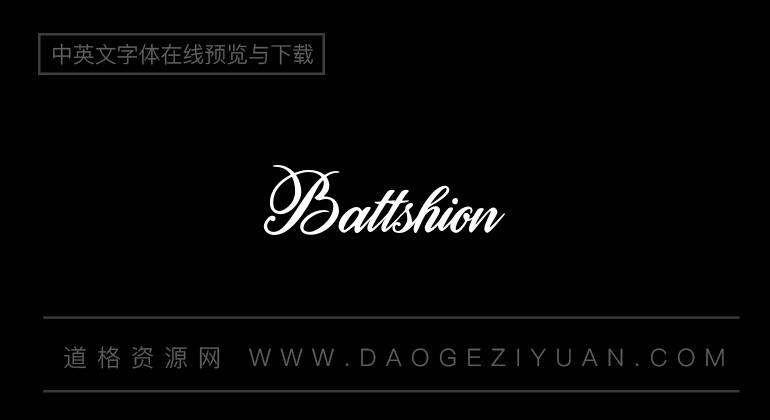
Battshion
Battshion 字体是一款英文细体字体,由英国设计师 Matthew Carter 于1998年设计,受到了传统英文细体字体的启发,它采用了更新的设计理念,以及更加精细的笔画,使得字体拥有更高的可读性和可辨识度,同时也更加美观。它的字体特点是:字母间距紧凑,字体清晰,笔画细腻,字体精致,适合用于报刊、书籍、网页等文字编辑中。
Battshion是一款非常不错的手写艺术字体,具有很好的视觉感,适合于文化类的宣传设计、商业类品牌的广告和产品包装设计以及个性化文字排版等较多场景。